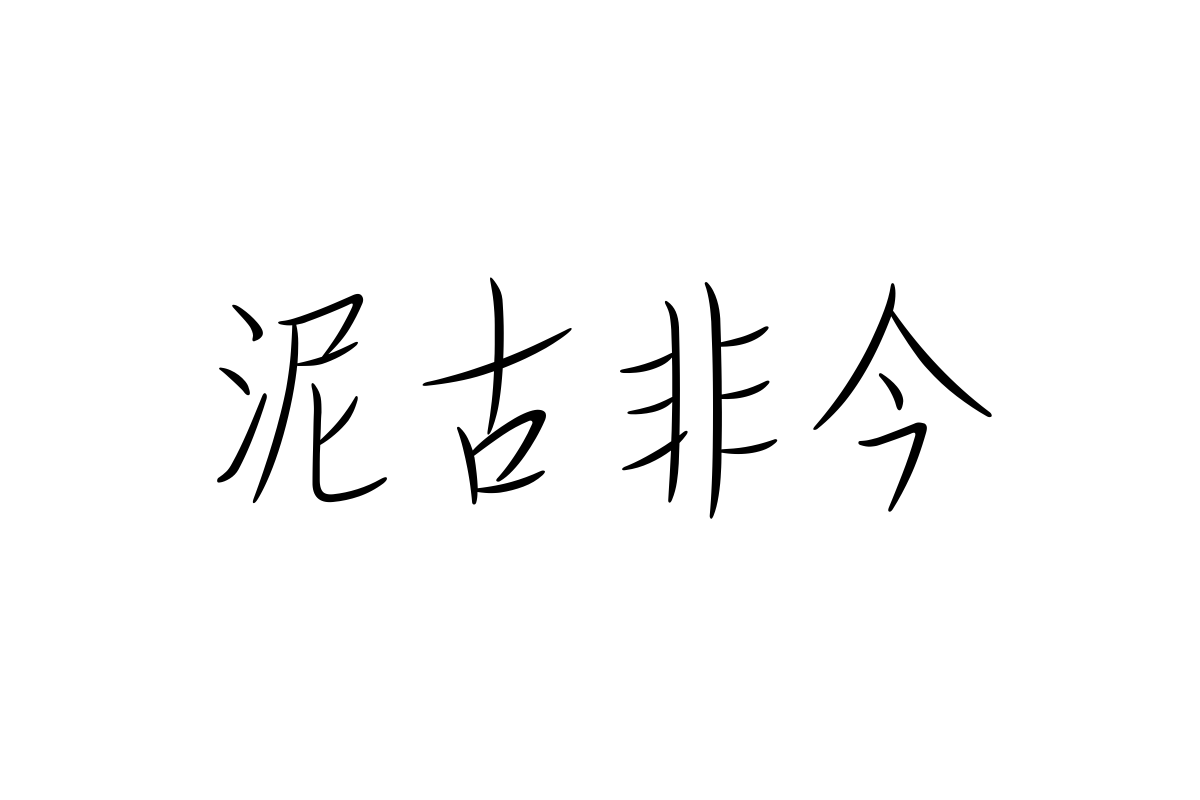
汉仪浅光 35W是一款由汉仪公司设计的字体,具有简洁、现代的设计风格。这款字体适用于各种需要简洁、易读的应用场景,如网站标题、广告牌、海报等。
汉仪浅光 35W的特点如下:
1. 字形清晰:该字体笔画流畅,字形结构紧凑,使得文字在视觉上显得清晰易读。
2. 风格独特:汉仪浅光 35W采用了简约而现代的设计风格,给人一种时尚、清新的感觉。
3. 适用范围广泛:这款字体适用于各种需要简洁、易读的应用场景,如网站标题、广告牌、海报等。
总之,汉仪浅光 35W是一款适合现代设计需求的字体,无论是用于品牌宣传还是其他商业用途,都能展现出独特的魅力。